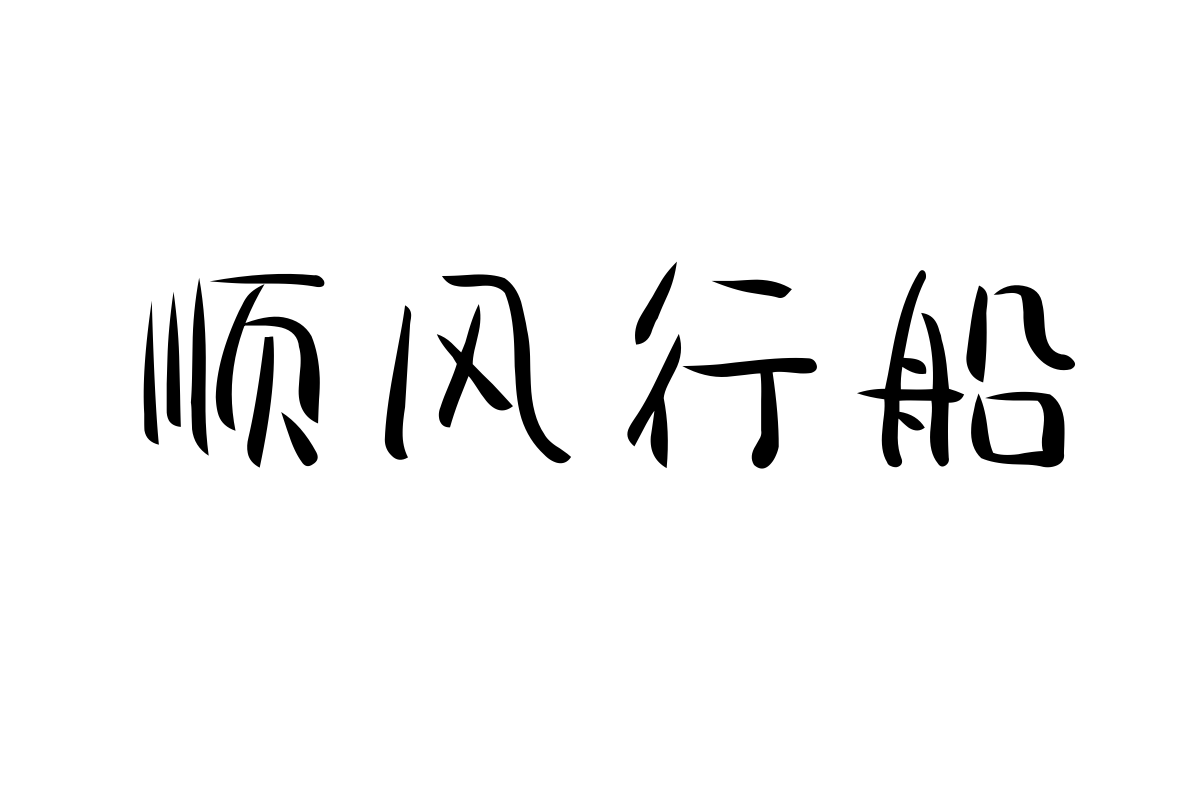
蝉羽青城体是一种具有独特风格和特点的字体,它结合了现代设计元素和传统书法艺术。这种字体的特点是笔画流畅、结构简洁、易于阅读,同时保留了一些传统的书法韵味。
蝉羽青城体的笔画粗细适中,线条清晰,给人一种优雅而有力的感觉。它的字形结构紧凑,但不失灵动,使得整个字体既有美感又不失实用性。此外,蝉羽青城体还注重字与字之间的间距和行距,使得整体布局更加协调和美观。
总的来说,蝉羽青城体是一种兼具传统与现代、简洁与美感的字体,适合用于各种需要展示文字信息的场合,如广告、海报、书籍等。